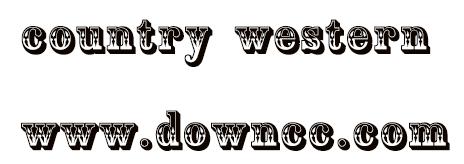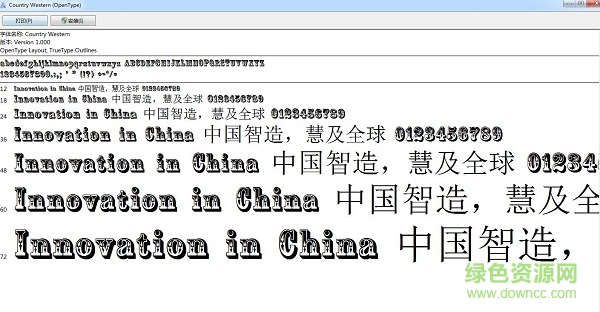
軟件介紹 軟件標簽: western字體 英文字體 country western和western兩款字體是本站為需要的朋友搜集的免費英文字體,country western字體外形獨特,黑白相間,整體呈漸變色,非常醒目,需要的朋友快來下載吧!高品質英文字體推薦opensans-extrabold 授權:免費軟件 WinAll, WinXP, Win7大?。?.4M語言:中文opensansextrabold字體是一款超粗的英文字體,屬于人文主義無襯線字體,字面清晰,易認好用,風格明顯,用作屏幕顯示效果非常好,歡迎大家免費下載!人文主義體介紹這些字體是無襯線字體中最具書法特色的,有更強烈的下載地址agenda bold字體 授權:免費軟件 WinAll, WinXP, Win7大小:350KB語言:中文agenda系列字體包收錄了agendabold字體、agendalight字體、agendasemibold字體、agendamedium字體等多款高品質的無襯線字體,外形美觀,富有韻律,有需要者歡迎前來免費下載!字庫分類【按編碼】:GB2312、GBK、GB下載地址英文字體組成一個完整的TTF、otf、ttc字體有基本拉丁文(字母A-Z大小寫、常用符號)、擴展拉丁文(音標、注音符號)、圖形符號、控制符號以及其他很多部分組成,不過通??梢灾谱髦话纠∥膮^(qū)的字體。western字體安裝方法1、點擊打開字體,直接選擇安裝即可。2、將字體復制到C:\Windows\Fonts文件夾即可完成安裝。 軟件截圖 上一張下一張(1 / 1) 安裝詳細截圖 其他版本下載 標題 大小 更新日期 下載 下載地址 電腦版 western字體 點擊報錯 軟件無法下載或下載后無法使用,請點擊報錯,謝謝! 關閉報錯反饋 請描述您所遇到的錯誤,我們將盡快予以修正,謝謝! *必填項,請輸入內容 本類最新 sounso beauty字體 spyced哥特英文字體 ttf版 zerodegrees字體 the next font ttf版 coolvetica font keep calm ttf 免費版 相關文章 用CMailServer打造郵件服務器 SQL-SERVER 聲明游標 Access數(shù)據(jù)庫安全的幾個問題 通過ASP與ACCESS數(shù)據(jù)庫建立連接(附源碼)(3) 通過ASP與ACCESS數(shù)據(jù)庫建立連接(附源碼)(2) 通過ASP與ACCESS數(shù)據(jù)庫建立連接(附源碼)(1) 用戶評論 熱門評論 最新評論 發(fā)表評論 查看所有評論(0) 昵稱: 請不要評論無意義或臟話,我們所有評論會有人工審核. 字數(shù): 0/500 (您的評論需要經過審核才能顯示)